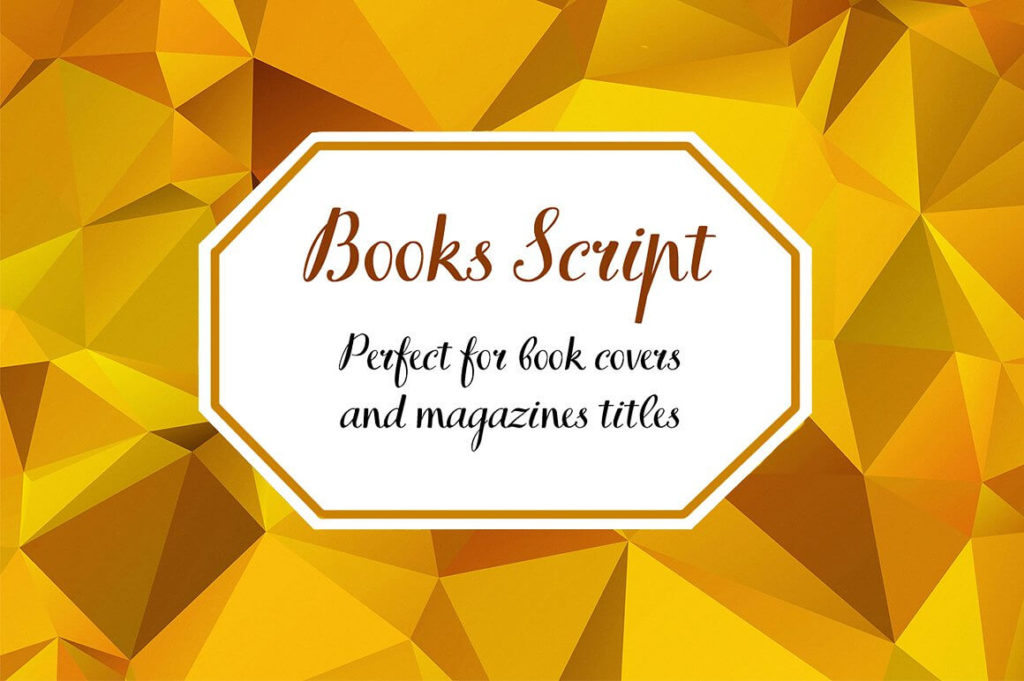
это элегантный рукописный гротеск (script), созданный Иваном Гладких и выпущенный студией TypeType в 2015 году. Вдохновленный книжной типографикой советского периода 1960–1970-х годов, он сочетает в себе ритмичность и эмоциональность, сохраняя при этом теплоту и человечность почерка. Идеально подходит для создания иллюстраций, детских книг и акцентных заголовков. Если вы ищете уникальный шрифт с характером, **скачать бесплатно** его можно на нашем сайте (для ознакомления), но важно помнить о лицензионных ограничениях при коммерческом использовании кириллических текстов